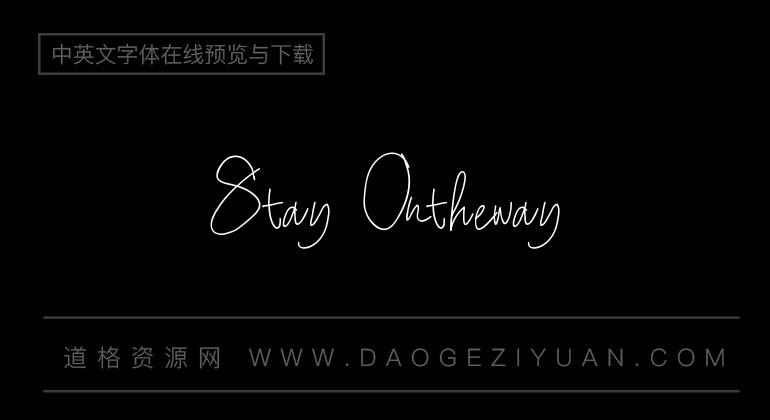
Stay Ontheway
Stay Ontheway 是一种现代风格的书法字体,由日本设计师手写制作。这种字体具有简单、流畅、稳定的特点,适合用于海报、广告、标语、包装等设计领域。Stay Ontheway 字体的特点是紧凑的字距、倾斜的字形和不规则的笔画,这使其在设计中具有独特的个性和视觉冲击力。此外,它还支持多种语言文字,包括拉丁字母、希腊字母和西里尔字母等,可以满足不同语言使用者的需求。
Stay Ontheway是一款非常不错的手写艺术字体,具有很好的视觉感,适合于文化类的宣传设计、商业类品牌的广告和产品包装设计以及个性化文字排版等较多场景。